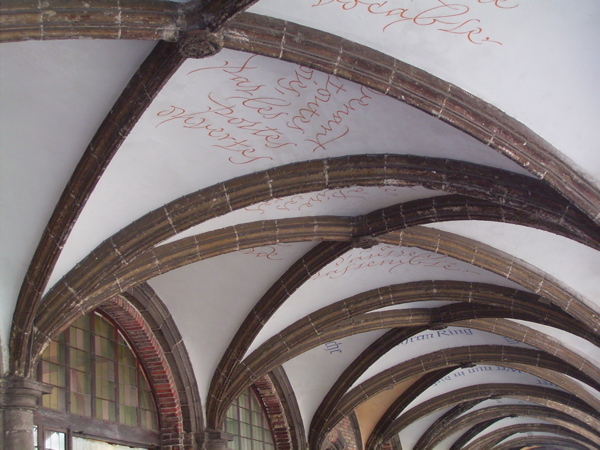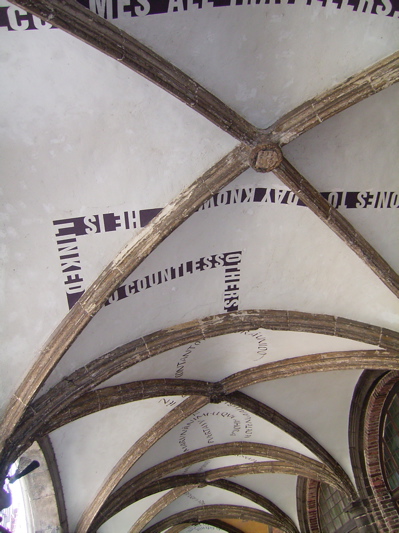
壁や天井にも!
いつもは平面の紙に文字を書いていますが、本当は「文字」なのだから、どこにでも書こうと思えば書けるのです。道具や画材を変えればいい訳です。
これは、ブリュージュのCVさんのお宅。お夕飯の時間にお邪魔してじっくり彼女のお宝を見せてもらいました。夢の様な時間だったと、今でも思い出してはウットリ・・・・。
家の中にこんな美しい文字があったらなぁ。これは梁に書かれた文字です。フラマン語なのでしょうかね。もしやオランダ語としてでも訳せるかなと思い、和蘭ー英語の自動翻訳機で調べてみたら、こんな風に英語が出て来ました
And if the long chronicle on its end runs nothing has been completed
う〜む英語でもよくわからないですなぁ・・・・。どなたかおわかりになりますか??
家族と共に長い時間を過ごす家の歴史のことについてなのかなぁ。
他にもあります。ブリュージュでは有名なこの天井の文字。
実際、はしごを持って来てそれに乗り、ひたすら上を向いて書いたそうです。さぞかし大変だったことでしょうね。お疲れさまです。
平らな机の上でも文字を書くのは大変なのに、上を向いて書くなんて。一体どんな道具で書いたのでしょうか。ペンではないことは確かでしょう。平筆やポインテッドブラッシュ?でも明らかにブロードエッジの道具で書いたらしき文字もありますね。
紙ばかりではなく、どこか天井や梁や壁にも文字を書いてみたいですよね!でもなかなかそれを試す訳にもいきません。
でも、みなさま。我が家でも思いきって家に文字を書こうと言う方!朗報です。